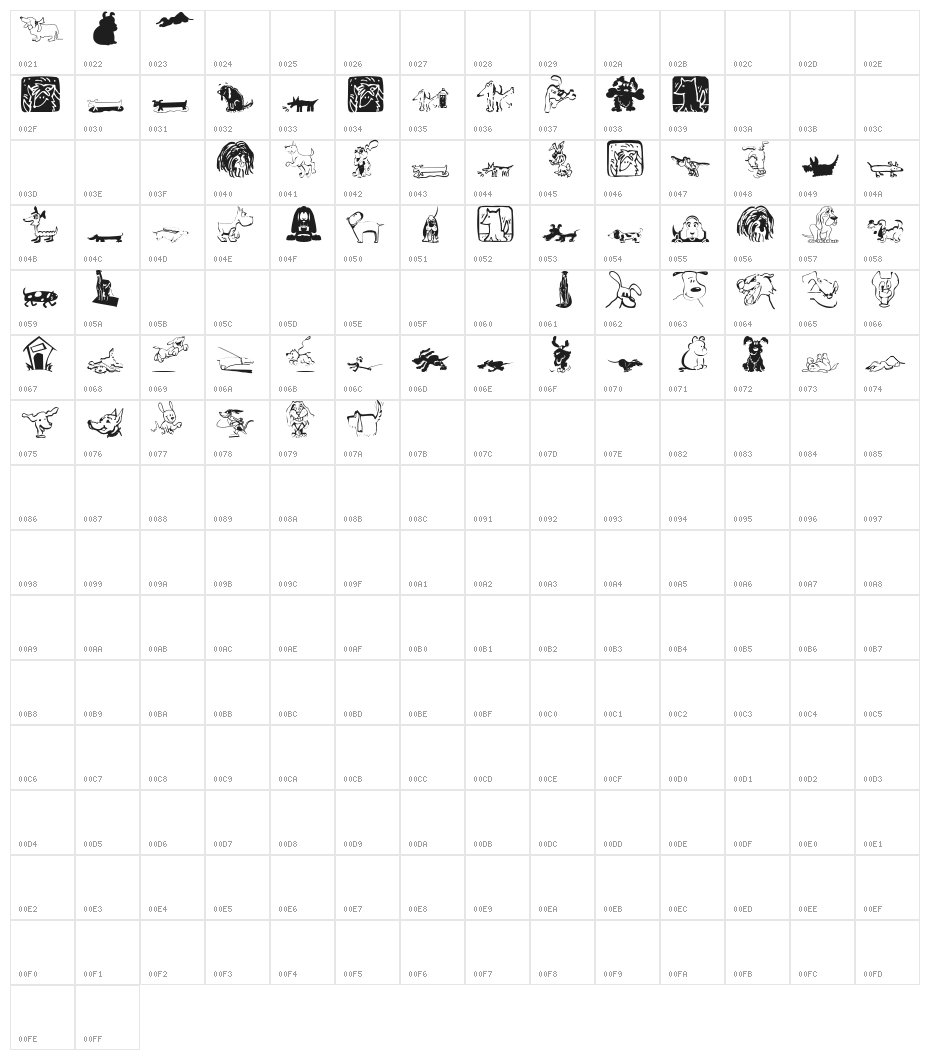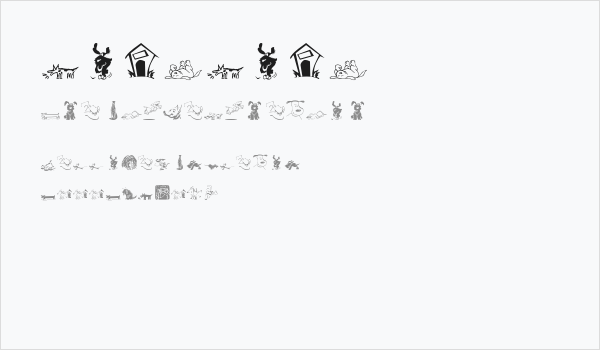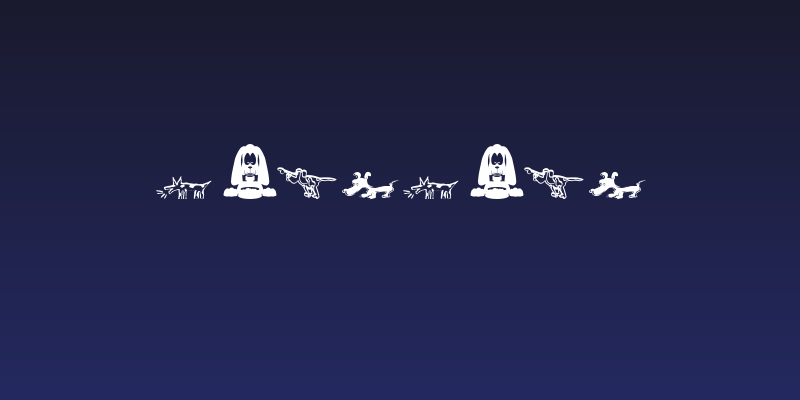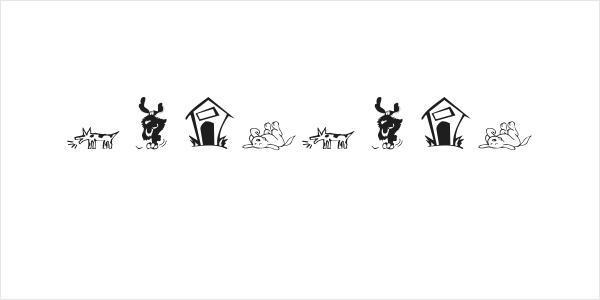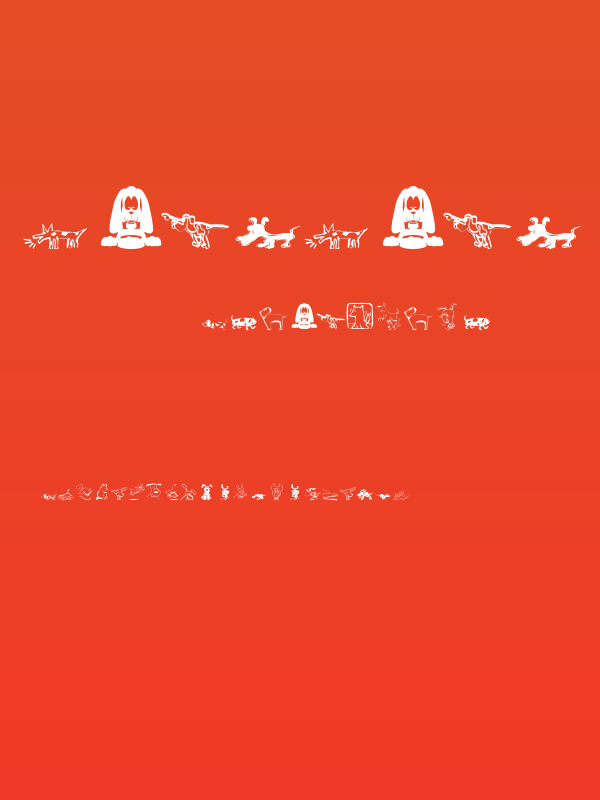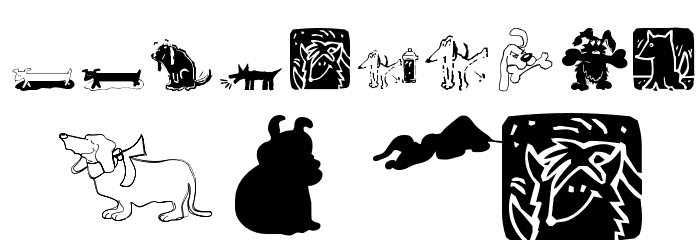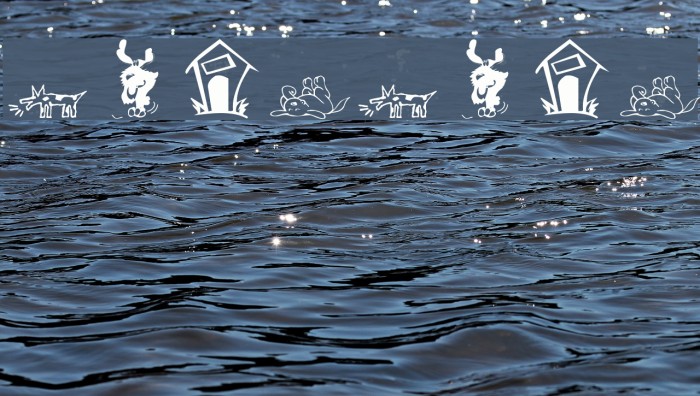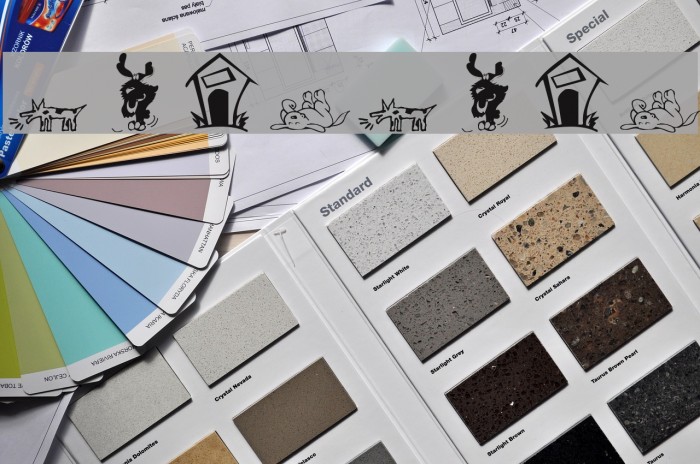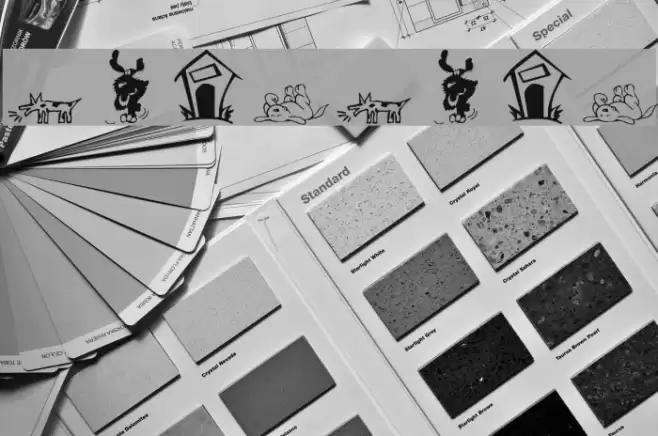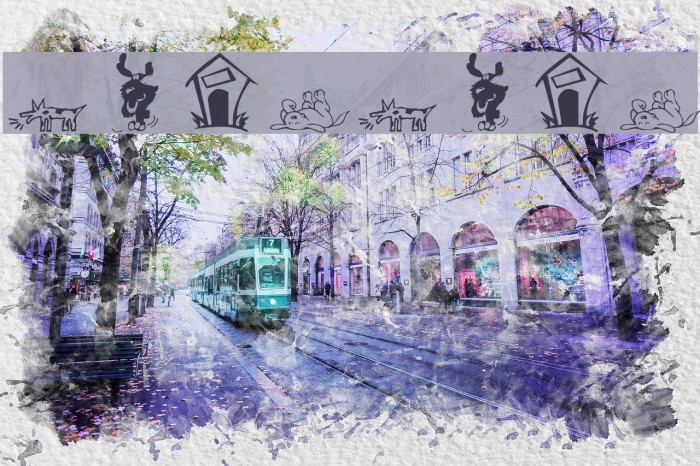
DogsDogs Font
| Stile generale | Playful, Whimsical, Decorative |
| Caso d'uso | Illustrative elements, Decorative accents, Themed graphics |
| Progetti proposti | Children's books, pet shop branding, greeting cards, playful posters, educational materials, scrapbooking. |